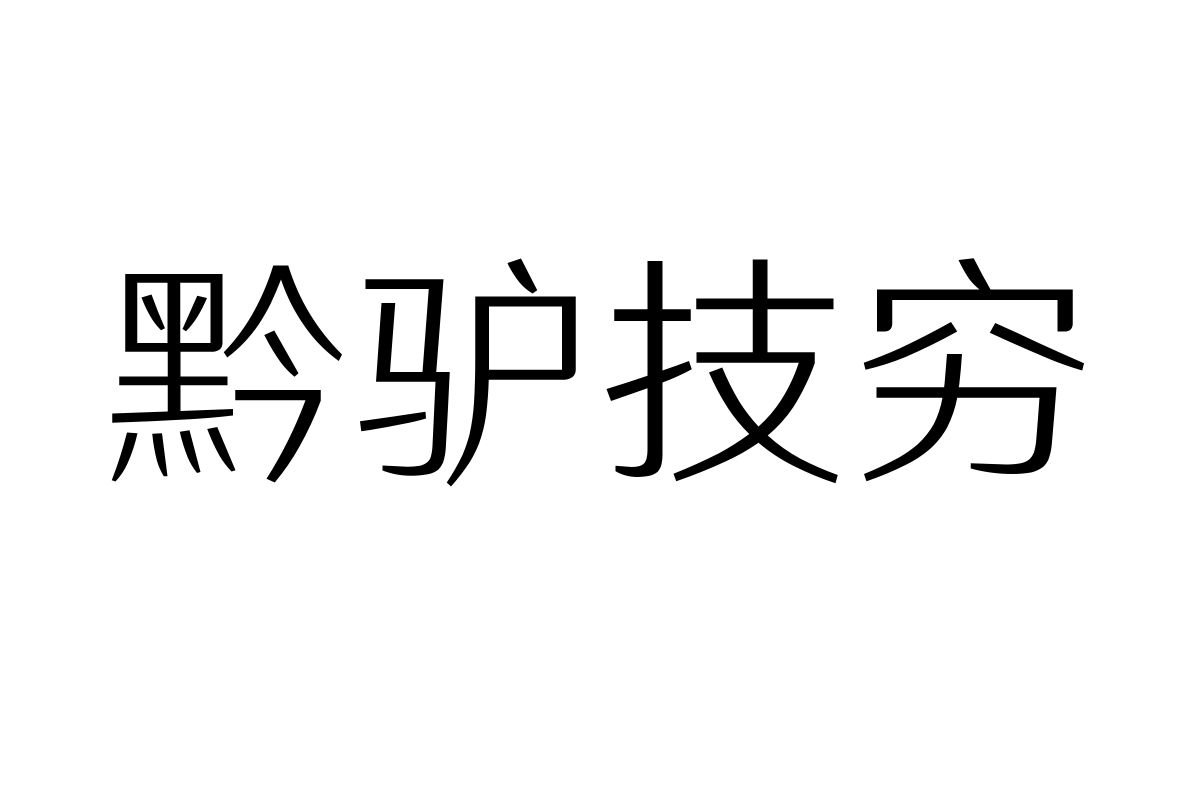
汉仪文黑-35是一款具有现代感和简洁风格的字体。它由汉仪字库出品,适用于各种设计场景,如标题、正文、广告等。这款字体的特点是笔画流畅、字形端正、易于阅读。它的笔画粗细适中,既不会过于粗犷也不会过于纤细,给人一种舒适的感觉。同时,这款字体的字形也相当规整,没有过多的装饰性元素,使得整体看起来更加简洁大方。